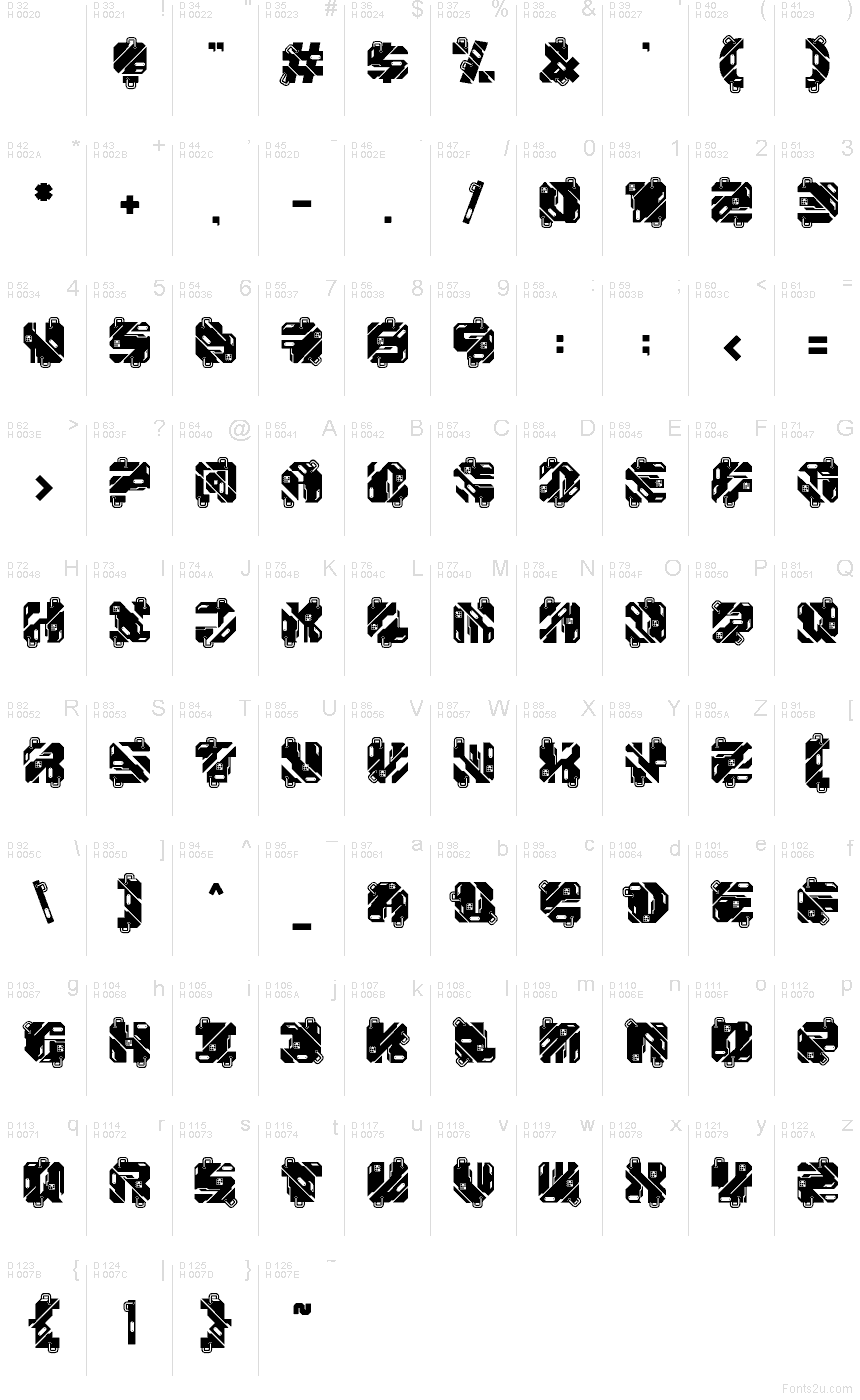
Space Sparkle Six od Putracetol Studio je bezplatné sci-fi písmo pro nadpisy, které vypadá jako sestavené z dílů vesmírné stanice. Díky diagonálním řezům, zaobleným detailům připomínajícím průzory a drobným mřížkám včleněným do znaků působí design konstruovaným, orbitálním dojmem, nikoliv jen jako běžná technická plocha.
Font nejlépe vynikne v herních titulech, grafice pro streamování, plakátech na akce, náhledech videí na YouTube a tematických obalech, kde tyto vesmírné prvky pomáhají vyprávět příběh. Nejvíce těží z krátkých nadpisů a log, protože vyříznuté sekce a detaily poklopů mění každé slovo v kompaktní kus environmentálního designu.